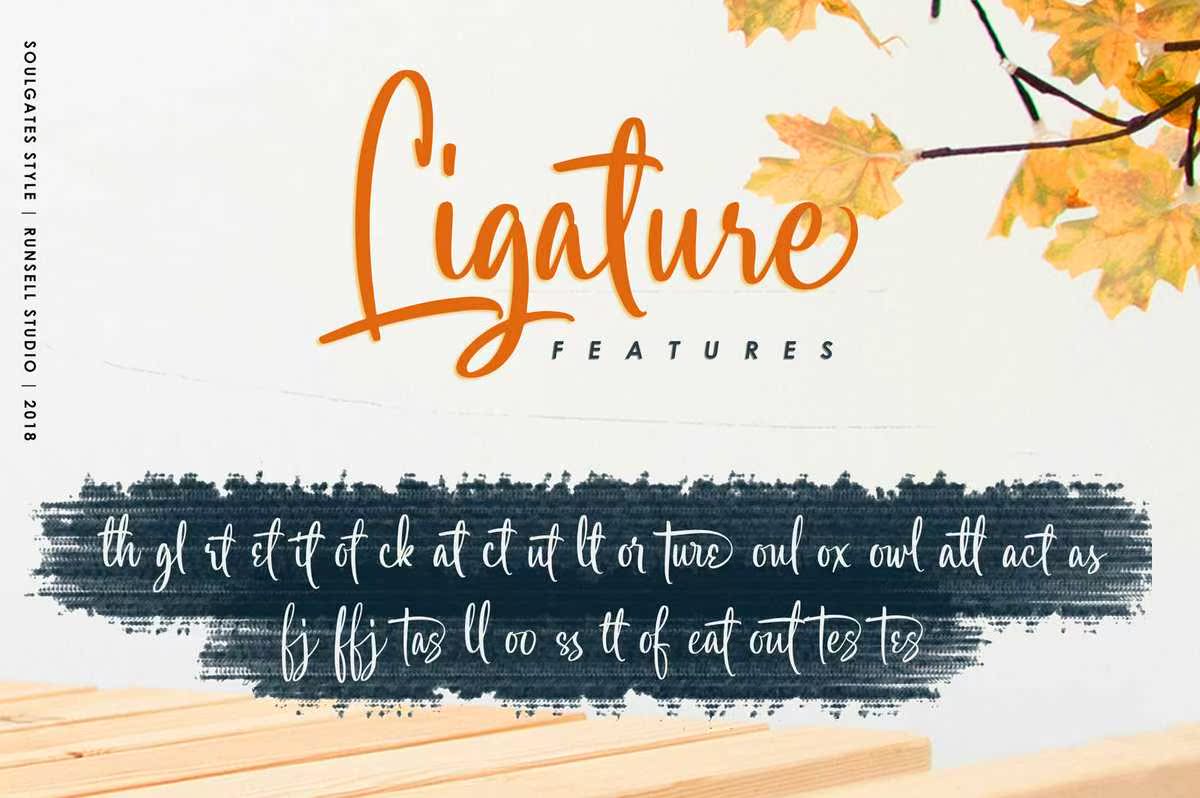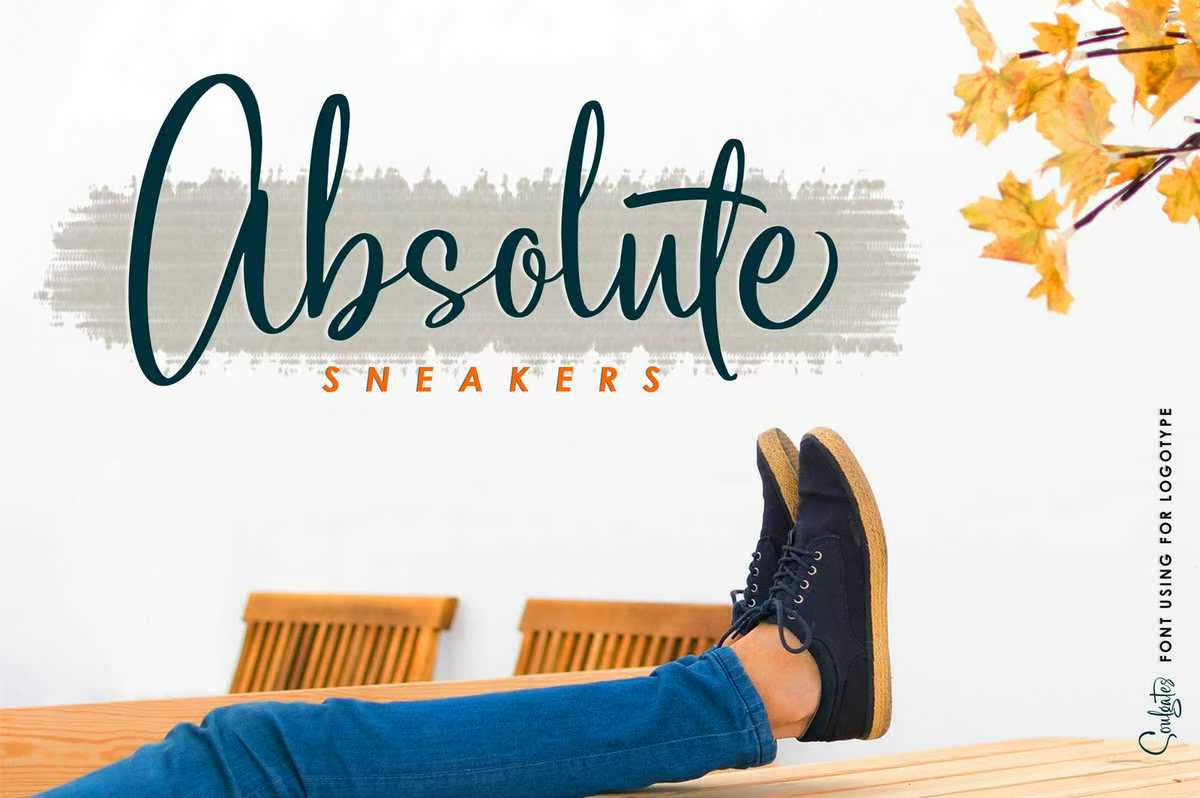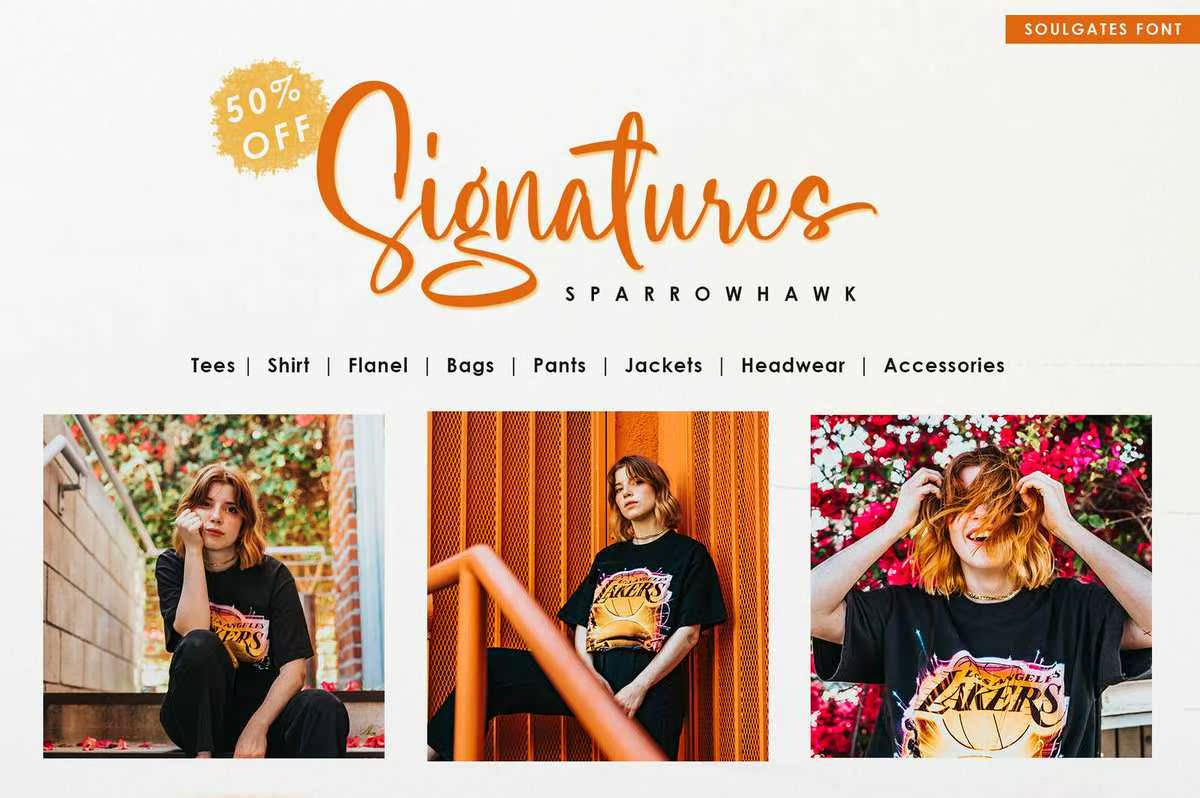
SoulgatesIsabrushScriptTypeFacewheverySingleLetters包含BeautifulCharacterAlternates。此字体包含70多个连字、上下文替换和样式替换。这些内容将使您的项目更加规范和独特。SoulgatesIsabrushScriptTypeFacewheverySingleLetters包含BeautifulCharacterAlternates。此字体包含70多个连字,上下文替换和风格替换。aclassy内容将使您的项目看起来更加现代和独特。